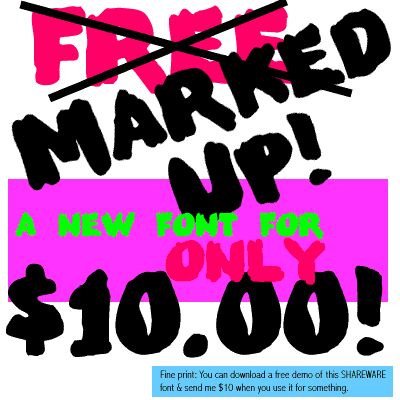
Marked Up von S. Roland Frantz aus dem Jahr 1999 ist eine kostenlose Pinsel-Schrift mit einer breiten, malerischen Silhouette und abgerundeten, unregelmäßigen Kanten. Die Zeichen wirken kompakt und handgemacht, mit weichen Wölbungen und stumpfen Enden – so sieht das Wort aus, als wäre es wirklich gepinselt und nicht aus ordentlichen Teilen zusammengesetzt.
Die Schrift hat genug Charakter für Plakat-Überschriften, Musik-Flyer, Veranstaltungsbanner und Sticker-Art, wo die unebenen Pinselformen kurze Texte perfekt zur Geltung bringen. Dank der rauen Kanten eignet sie sich zudem hervorragend für Produktetiketten und Zines, die einen handgemalten Look statt steriler Überschriften suchen.